Font chữ sang trọng là nhóm font được thiết kế với đường nét tinh tế, cân đối và có tính thẩm mỹ cao, thường dùng để tạo cảm giác cao cấp, chuyên nghiệp và đẳng cấp trong thiết kế. Các font này thường xuất hiện trong logo thương hiệu, thiệp cưới, poster, bao bì sản phẩm, catalogue, website thời trang, mỹ phẩm, nội thất hoặc các ấn phẩm cần thể hiện sự thanh lịch. Việc lựa chọn đúng font chữ sang trọng không chỉ giúp nội dung dễ nhìn hơn mà còn góp phần nâng tầm hình ảnh thương hiệu và tạo ấn tượng mạnh với người xem ngay từ cái nhìn đầu tiên.
1. Prestigious
Prestigious là font serif sang trọng, kết hợp giữa nét đẹp cổ điển và hiện đại. Font này thường được dùng cho thiệp cưới, bìa tạp chí, hình ảnh mạng xã hội, bộ nhận diện thương hiệu và các thiết kế muốn truyền tải cảm giác đẳng cấp, tinh tế.
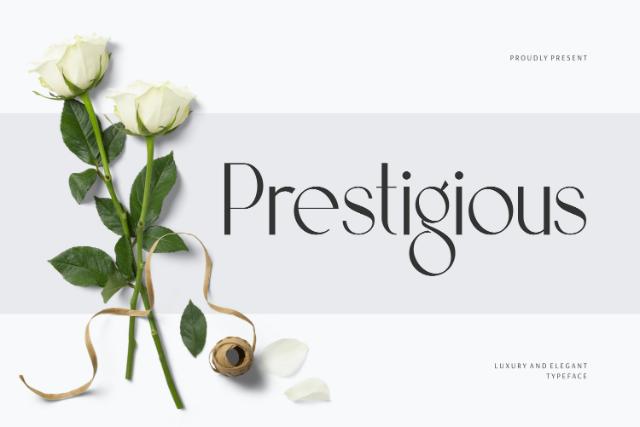
2. Adelaide
Adelaide là font chữ serif mang phong cách thanh lịch, nổi bật ở sự chuyển đổi mềm giữa nét thanh và nét đậm trong từng ký tự. Kiểu chữ này tạo cảm giác bóng bẩy, chỉn chu và rất phù hợp với thiết kế bao bì, logo, website hoặc các ấn phẩm cần vẻ ngoài cao cấp.
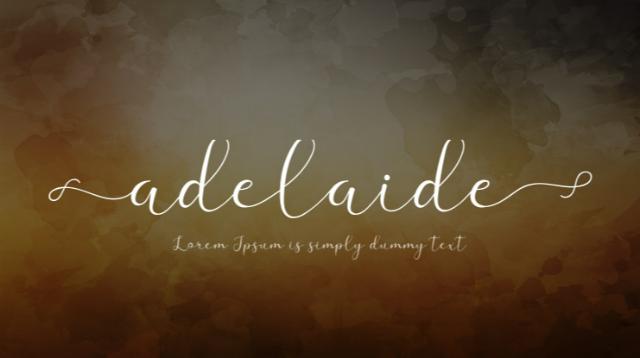
3. Manhattan
Manhattan là font serif có nét chữ thanh mảnh, gọn gàng và dễ phối hợp với nhiều font khác. Đây là lựa chọn phù hợp cho tiêu đề chính, tiêu đề phụ hoặc các thiết kế thương hiệu cần truyền tải thông điệp một cách sang trọng, rõ ràng và chuyên nghiệp.
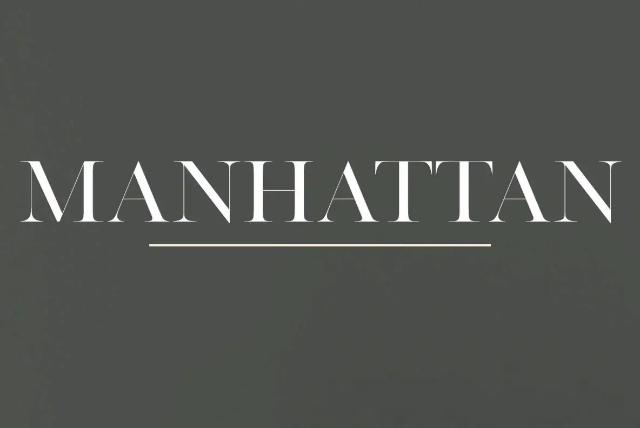
4. Karatone
Karatone là font serif tao nhã, được nhận diện bởi các đường cong mềm mại và bố cục chữ gọn gàng. Font này phù hợp với thiết kế logo, bìa sách, nhãn sản phẩm, bao bì thời trang và mỹ phẩm, đặc biệt khi cần tạo cảm giác tinh tế nhưng vẫn dễ đọc.
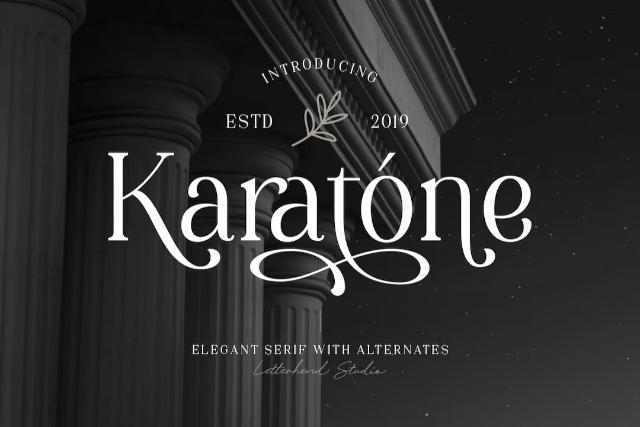
5. Bodoni
Bodoni là font serif nổi tiếng thuộc nhóm Didone, được thiết kế bởi Giambattista Bodoni vào thế kỷ 18. Đặc điểm chính của Bodoni là độ tương phản cao giữa nét thanh và nét đậm, tạo cảm giác cổ điển, trang trọng và học thuật. Font này thường được dùng cho tiêu đề, sách xuất bản, tài liệu in ấn và các thiết kế cần sự nghiêm túc.
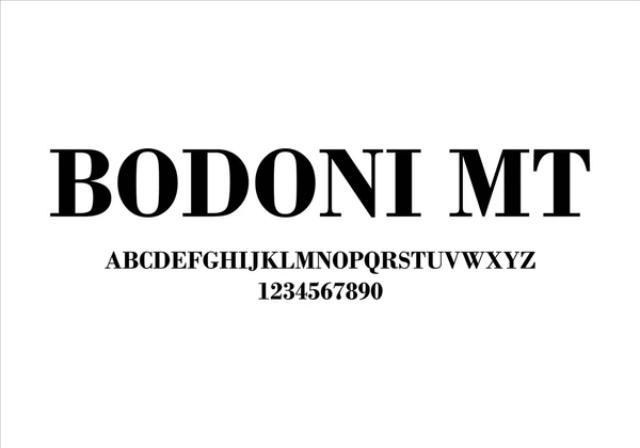
6. Elaris
Elaris là font serif mang vẻ đẹp thanh lịch, hiện đại và có tính thời trang cao. Kiểu chữ này phù hợp với các thiết kế về lifestyle, thời trang, làm đẹp hoặc những ấn phẩm cần cảm giác nhẹ nhàng, tinh tế nhưng vẫn đủ nổi bật để thu hút người xem.
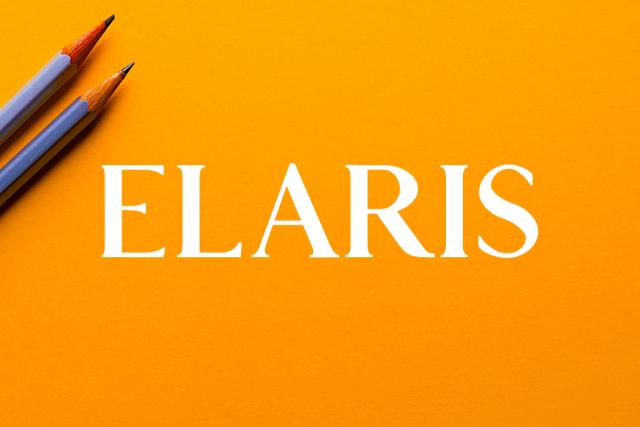
7. Novante
Novante, tên đầy đủ là Novante Elegant Display Serif, là font chữ in hoa hoàn toàn, lấy cảm hứng từ phong cách Art Deco kết hợp tối giản hiện đại. Font này phù hợp với branding, logo, tiêu đề tạp chí và các thiết kế cần vẻ ngoài ấn tượng, thời thượng.
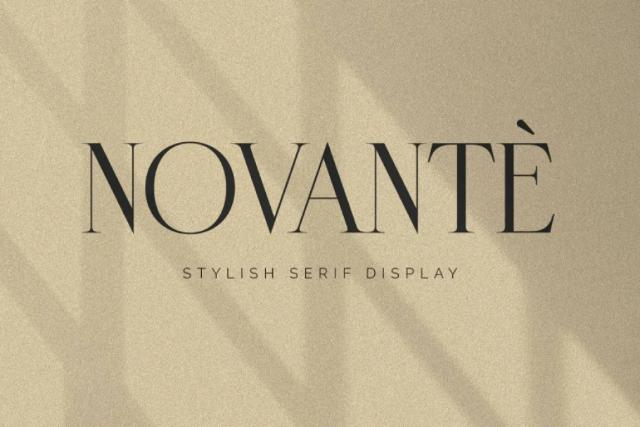
8. Leyton
Leyton là font serif hiện đại, có vẻ đẹp quyến rũ và khác biệt hơn so với nhiều font serif truyền thống. Font này thích hợp để dùng cho headline, tiêu đề phụ, poster, banner hoặc các thiết kế cao cấp cần điểm nhấn thị giác mạnh.
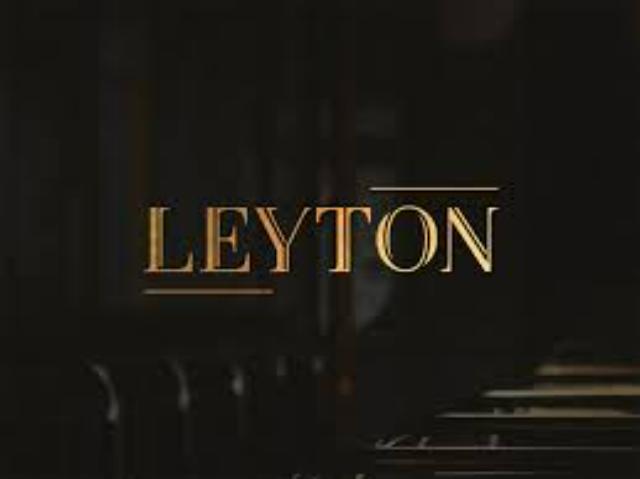
9. Kenilla
Kenilla là font serif hiện đại, nổi bật với phần đuôi chữ mượt mà, đường cong uyển chuyển và dáng chữ gọn gàng. Font này phù hợp với logo, tiêu đề tạp chí, bao bì trang sức, thiệp mời và các thiết kế mang hơi hướng vintage sang trọng.
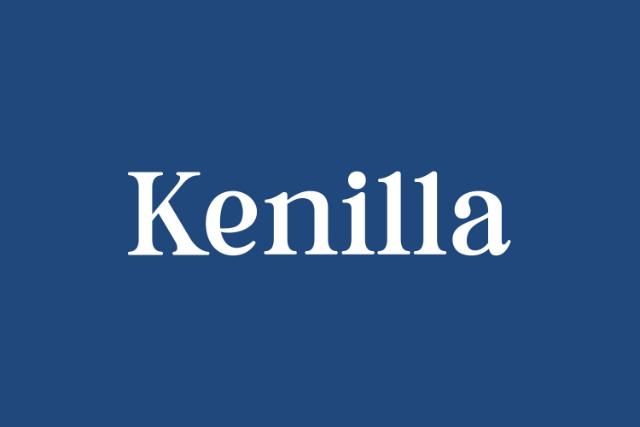
10. Marschel
Marschel là font serif lấy cảm hứng từ phong cách La Mã, mang vẻ đẹp lãng mạn và cổ điển. Các đường cong thanh nhã giúp font này phù hợp với thiết kế logo, tiêu đề, bộ nhận diện thương hiệu và những ấn phẩm cần tạo cảm giác nghệ thuật, cao cấp.
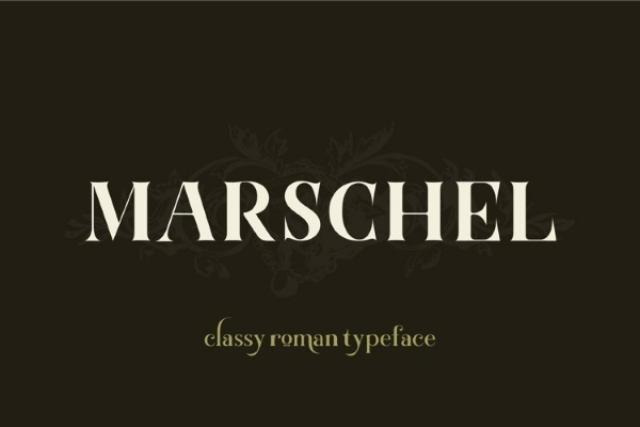
11. Halminton Grand
Halminton Grand là font serif có sắc thái mềm mại, sang trọng và dễ tạo điểm nhấn trong thiết kế. Font này thường phù hợp với branding, bảng hiệu quảng cáo, poster hoặc các sản phẩm thiết kế cần cảm giác tinh tế, chỉn chu và có tính thương mại cao.
12. New York
New York là font serif sang trọng với độ tương phản cao giữa nét thanh và nét đậm. Font này không quá cầu kỳ nhưng vẫn tạo cảm giác luxury rõ rệt, phù hợp với bưu thiếp, poster, bìa tạp chí thời trang, ảnh trang trí và các thiết kế cần sự thanh lịch.
13. Cabrito Didone
Cabrito Didone là font chữ có vẻ ngoài độc đáo với các đường cong lạ mắt, vừa tạo cảm giác vui nhộn vừa giữ được nét sang trọng. Font này phù hợp với thiết kế cao cấp, bài viết thời trang, lifestyle, tiêu đề tạp chí hoặc các ấn phẩm cần sự khác biệt.
14. Cotta
Cotta là font serif mang phong cách nữ tính, thanh lịch và hiện đại. Font này phù hợp với thiết kế website, logo, thiệp mời, tạp chí, bộ nhận diện thương hiệu và các dự án cần vẻ đẹp nhẹ nhàng nhưng vẫn sang trọng.
15. Addington CF
Addington CF là font serif linh hoạt, có nhiều kiểu dáng khác nhau nên có thể dùng cho cả tiêu đề và nội dung văn bản ngắn. Đây là lựa chọn phù hợp cho catalogue, website, bài giới thiệu thương hiệu hoặc các thiết kế cần tính chuyên nghiệp và dễ ứng dụng.
16. Vidaloka
Vidaloka là font serif được thiết kế để tạo điểm nhấn ở kích thước lớn. Font này có độ tương phản cao giữa nét thanh và nét đậm, giúp tiêu đề, banner, poster hoặc đoạn chữ cần highlight trở nên nổi bật và dễ thu hút ánh nhìn.
Tóm lại, font chữ sang trọng không chỉ giúp thiết kế trở nên đẹp mắt hơn mà còn góp phần thể hiện phong cách, giá trị và đẳng cấp của thương hiệu. Tùy vào mục đích sử dụng như thiết kế logo, thiệp cưới, poster, bao bì sản phẩm hay ấn phẩm truyền thông, bạn có thể lựa chọn font serif, font script hoặc font display phù hợp. Một font chữ sang trọng được chọn đúng sẽ giúp tổng thể thiết kế tinh tế hơn, dễ ghi nhớ hơn và tạo ấn tượng chuyên nghiệp trong mắt người xem.